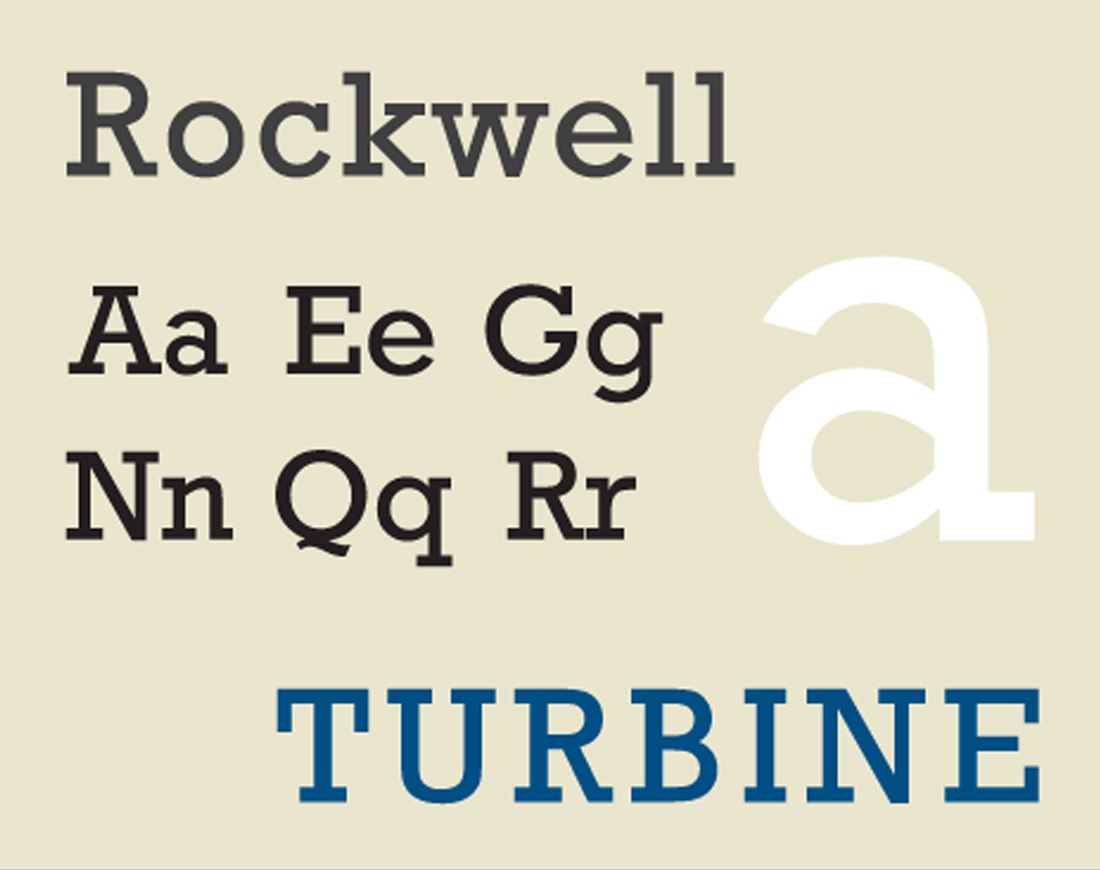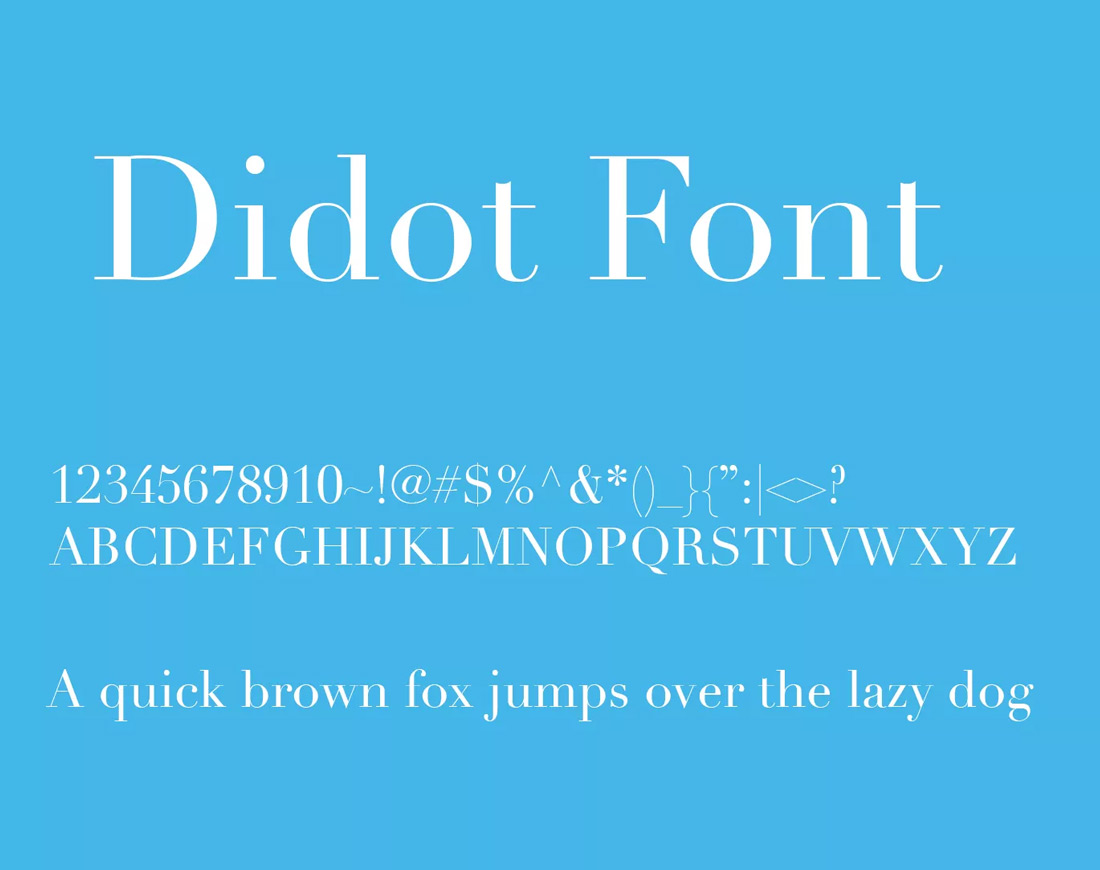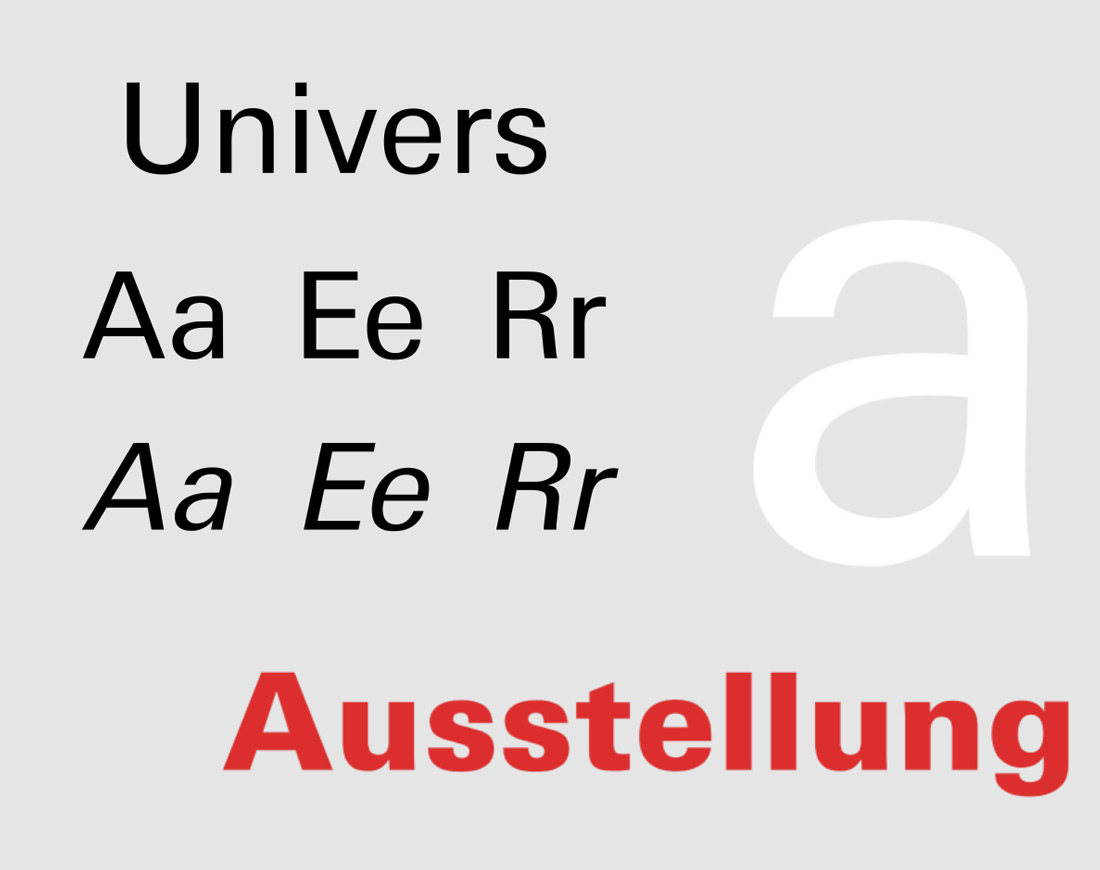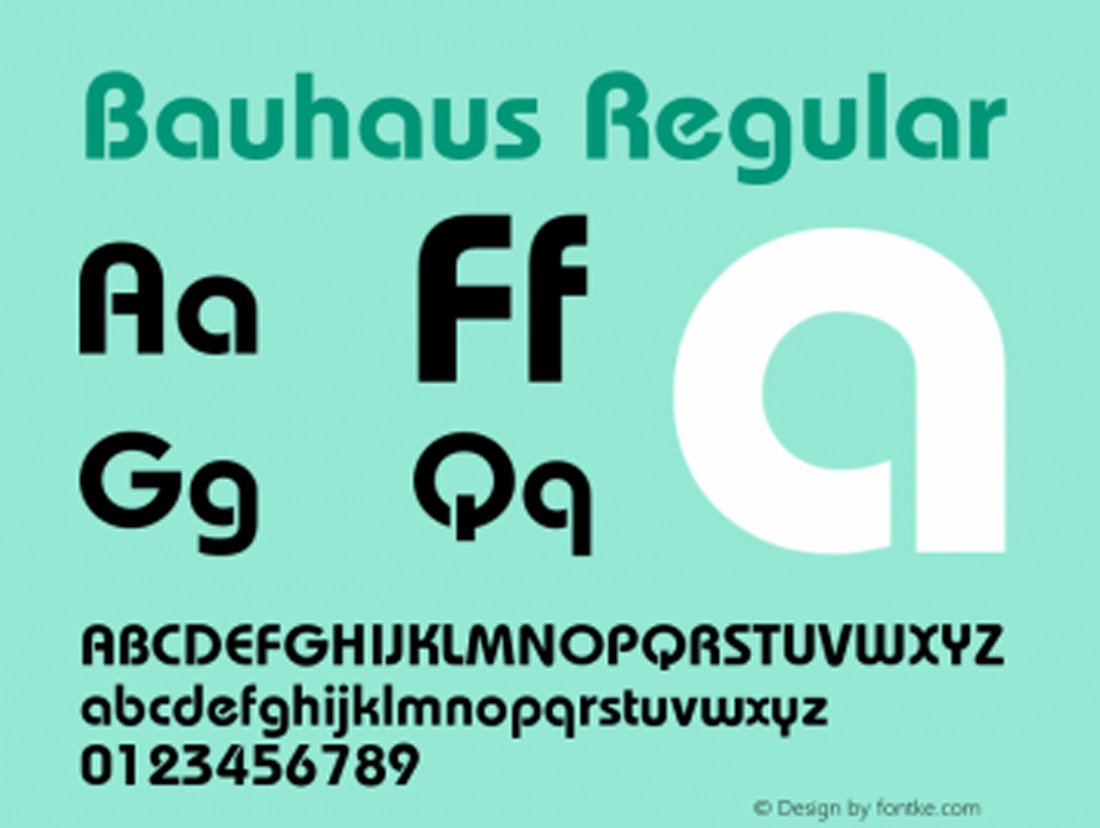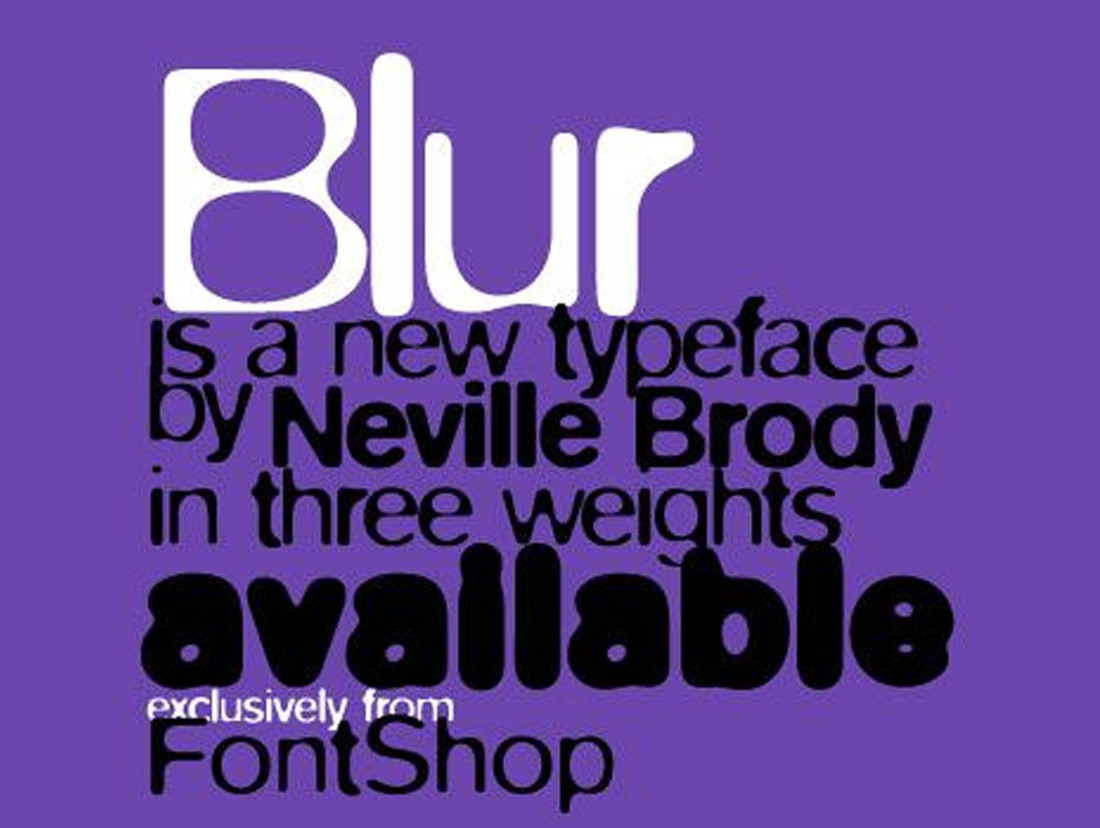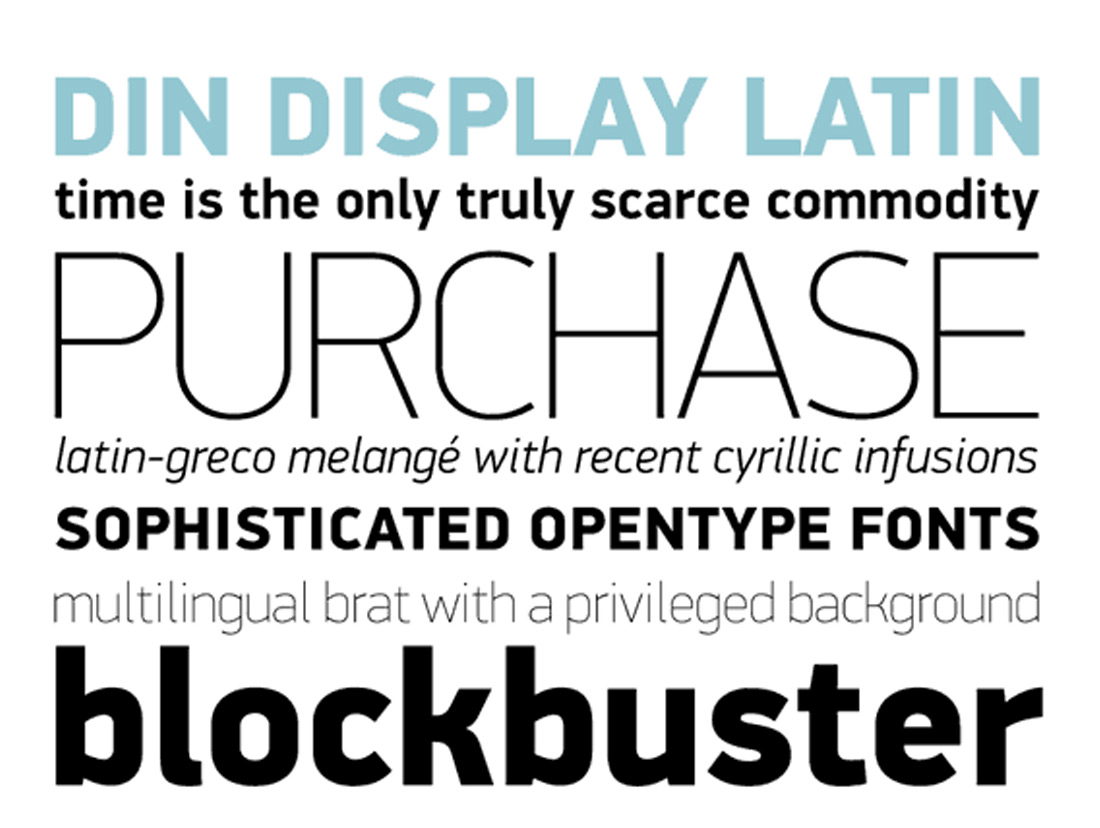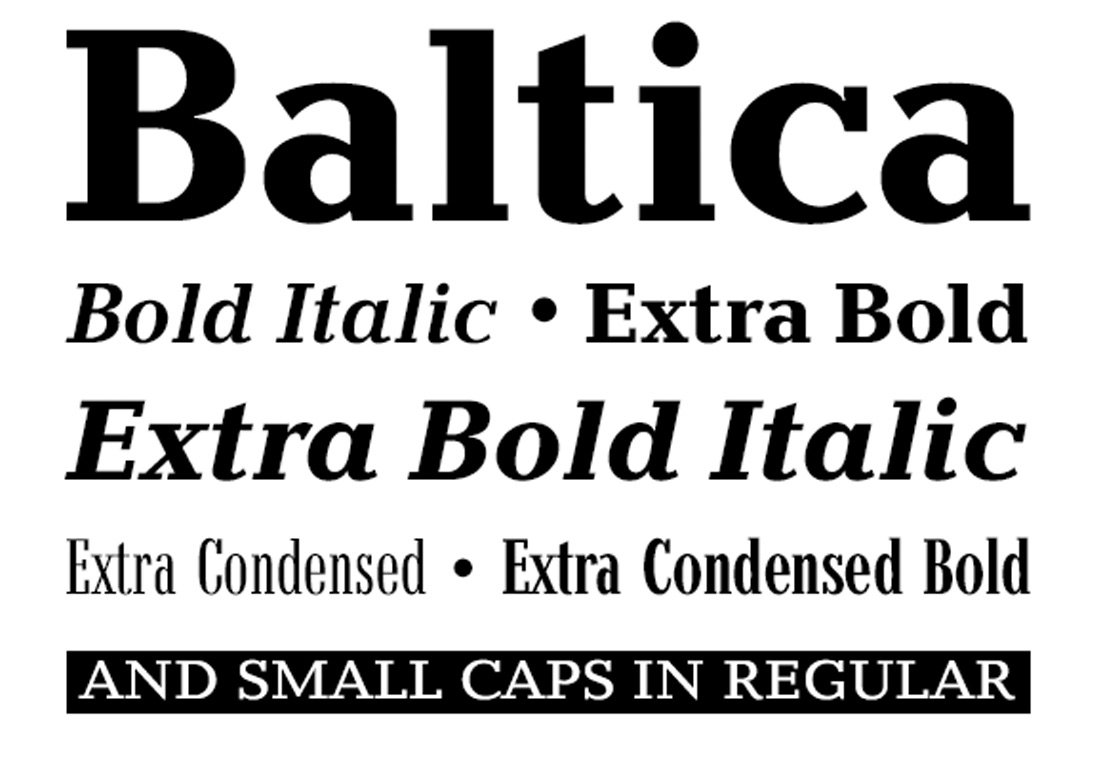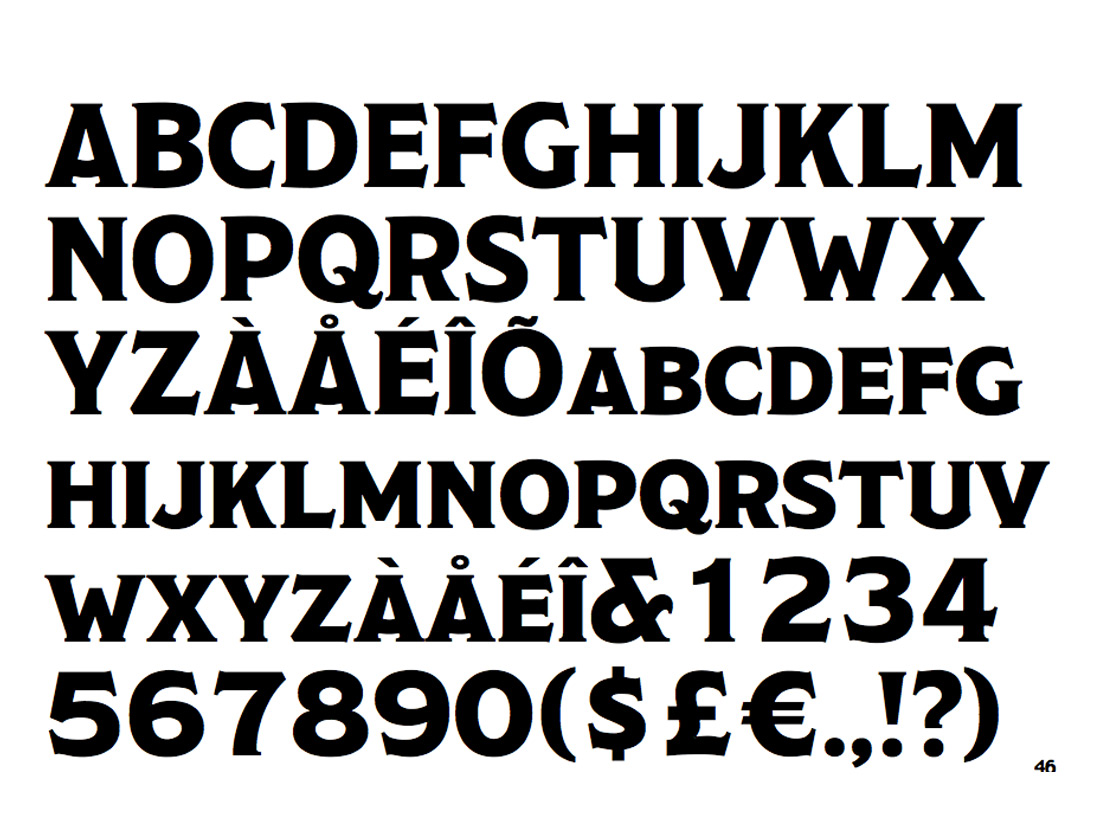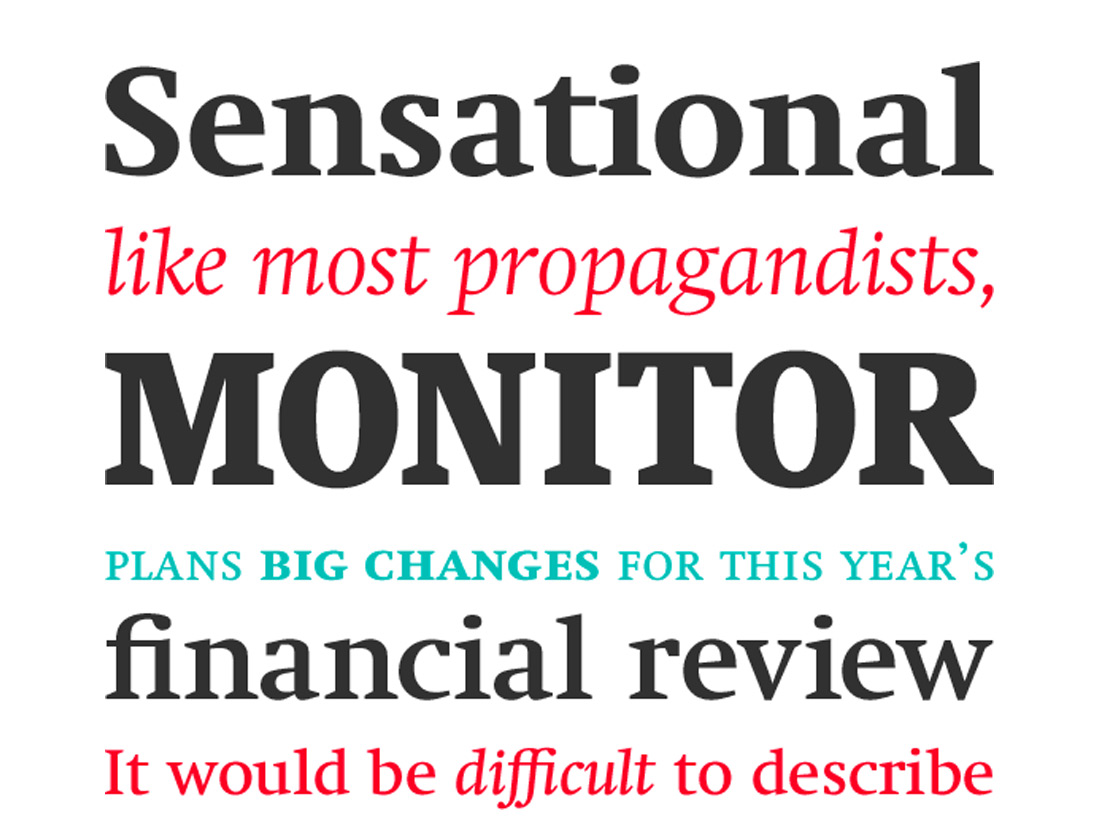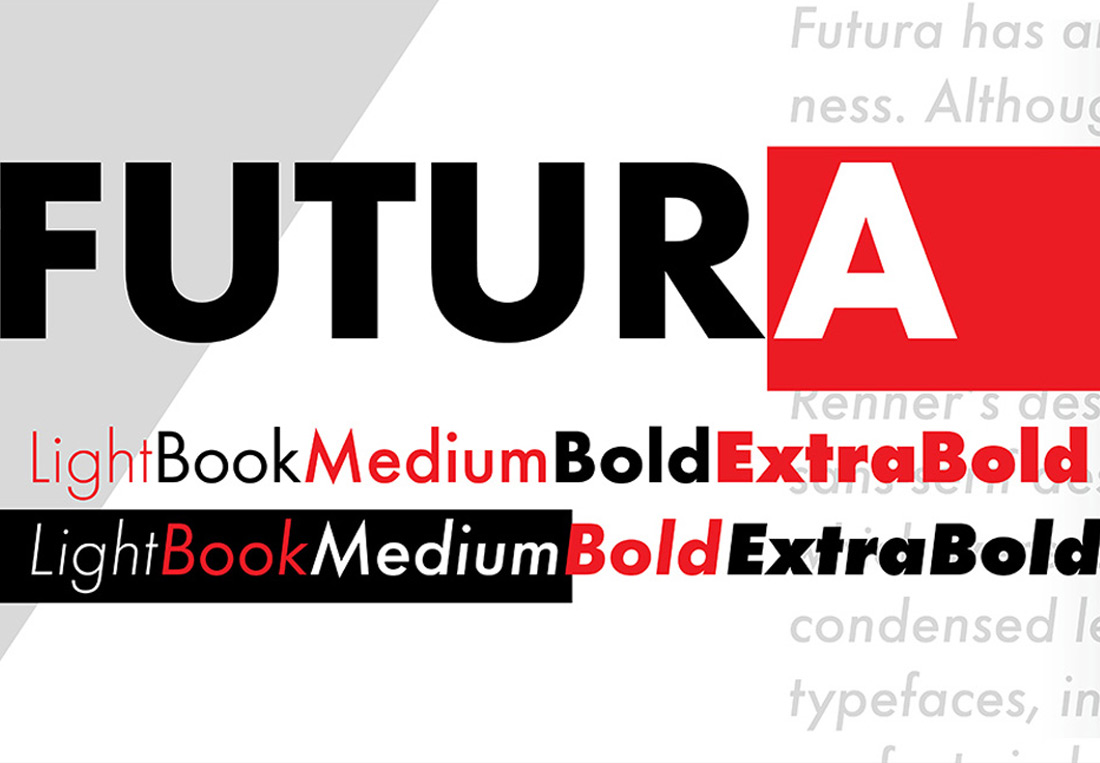
50 Logo-Schriftarten, die jeder Designer kennen sollte
‘Bei der Typografie geht es um die Funktion. Es reicht nicht aus, schöne Formen zu entwerfen.’ — James Todd
Oft denken wir an Farben und Bilder in grafischen Designs, insbesondere in Logos. Aber auch Logo-Schriftarten sind wichtige Gestaltungselemente. Tatsächlich sind viele ikonische Firmenlogos typografisch gestaltet. Wenn ein Logo einen Firmennamen hat, hängt der Erfolg seines Designs von der geschickten Verwendung von Schriften ab. Glücklicherweise ist eine breite Palette von Schriften verfügbar, um eine korrekte Wahl zu treffen.
Nur ein ausgebildeter und erfahrener Grafikdesigner kann eine derart perfekte Schrift in ein Design integrieren. Ein geschickter Designer versteht es, wie man mit einer konventionellen Schrift eine andere Form geben kann, um ein einzigartiges Design zu schaffen. So wurden beispielsweise die klassischen Schriftarten in vielen Logos neu gestaltet. Das Coca-Cola-Logo ist eines der besten Beispiele dafür, wie eine Schrift eine Markenidentität schaffen kann. Laut entrepreneur.com ist eine starke Typografie einer der wichtigsten Tipps für ein preisgekröntes Logo-Design, vor allem, weil die Schrift an sich schon als visuelles Element funktioniert.
Also, basiert Ihr Firmenlogo auf Typografie? Wenn ja, dann werfen Sie einen Blick darauf, ob sie die Leistungsfähigkeit der Schrift richtig nutzt. Stellen Sie sicher, dass die in Ihrem Firmenlogo verwendeten Schriften mit der Persönlichkeit Ihrer Marke übereinstimmen.
Eine gute Schriftart kann viel bewirken! Die Schriftart Ihres Logos spielt eine entscheidende Rolle bei der Gestaltung des Images Ihres Unternehmens. Ob Sie es glauben oder nicht, die Schriftart Ihres Logos erzählt eine Geschichte über Ihr Markenlogo, bevor die Worte es tun. Und Ihre Schriftwahl kann Ihr Logo-Design bestimmen oder brechen, unabhängig davon, ob es von einem Logo-Maker oder einem professionellen Designer erstellt wurde.
Aber bei so vielen verfügbaren Schriftarten im Web auf verschiedenen Plattformen kann es für einen Designer schwierig sein, eine Schriftart für ein Logo auszuwählen. Es gibt jedoch einige Schriften, die die Designer in ihrer Auswahl haben sollten, um einen guten ersten Eindruck zu hinterlassen!
Nachfolgend eine Liste von 50 Logo-Schriftarten, die jeder Designer kennen sollte
01. Garamond
Dies ist keine einzelne Schriftart, sondern eine Familie alter Serifenschriftarten. Diese Schriftart ist hervorragend lesbar und elegant, was sie zu einer perfekten Schrift im Designbereich macht. Zu den verschiedenen Schriften gehören Adobe Garamond, Stempel Garamond, EB Garamond, Sabon Next und ITC Garamond. Sie werden typischerweise in Zeitschriften, Websites, Lehrbüchern und langen Texten verwendet. Eine deutsche Publikation hat diese Schrift als die zweitbeste unter allen Schriften bewertet. Die Schriftart wurde erstmals 1989 veröffentlicht.
02. Helvetica
Helvetica ist eine der am häufigsten verwendeten Schriftarten in einer Vielzahl von Designs. Besonders Fachleute schätzen diese Schriftart. Seit 1984 ist Helvetica in PCs integriert. was einer der Gründe für ihre Beliebtheit ist. Viele Profis mögen und missbilligen diese Schrift aus einem einfachen Grund, weil die Buchstaben zu eng angeordnet sind. Für ein effektives Logodesign ist jedoch eine sorgfältige Auswahl der Schriftart erforderlich. Diese Schriftart kann nicht überall verwendet werden, um die gewünschte Nachricht zu übermitteln.
03. Trajan
Trajan wird seit langem in den Hollywood-Filmpostern verwendet. Die Schrift ist auch ein heißer Favorit für viele Designer, die Designs in Bezug auf Recht, Ehe, Religion und Dinge aus der Vergangenheit erstellen müssen. Trajan ist eine Serifenschrift im alten Stil und wurde 1989 von Carol Twombly entworfen. Das Design der Schrift basiert auf römischen quadratischen Kapitellen. Diese Schriftart gewährleistet die Vielseitigkeit Ihres Logodesigns.
04. Futura
Futura ist bekannt für ihre nahezu perfekten Kreise, Quadrate und Dreiecke, da sie auf geometrischen Formen basiert. Aufgrund der einzigartigen geometrischen Form werden große Displays, Corporate Designs, Bücher und Logos häufig mit dieser Schrift verwendet. Die Schrift wird von vielen als ideal für kleine Texte angesehen.
05. Bodoni
Wenn Sie auf der Suche nach einer idealen Schriftart für Überschriften, Logos und Dekorationstexte sind, dann ist Bodoni die perfekte Wahl für Sie. Sie hat flache und ungebrochene Serifen und eine schmale Grundstruktur. Es gibt sowohl dicke als auch dünne Striche in dieser Schriftart, und es gibt einen Kontrast zwischen den beiden. Die Schriftart wirkt durch ihre geometrische Konstruktion ästhetisch. Achten Sie darauf, dass Sie diese Schriftart besonders in Ihrem Design-Brief erwähnen, wenn Sie Ihre Designarbeit im Crowdsourcing durchführen.
06. Zorus Serif
Zorus Serif wurde von Jeremie Dupuis, einem kanadischen Designer, entworfen. Die antiken Glyphen der Schrift verleihen ihr ein ausgeprägtes gallisches Flair. Die Schriftart ist geeignet, wenn Sie Ihrem Design ein Gefühl von Druck und altmodischem Aussehen verleihen wollen. Sie können auf diese Schriftart in kursiver und Standardversion zugreifen.